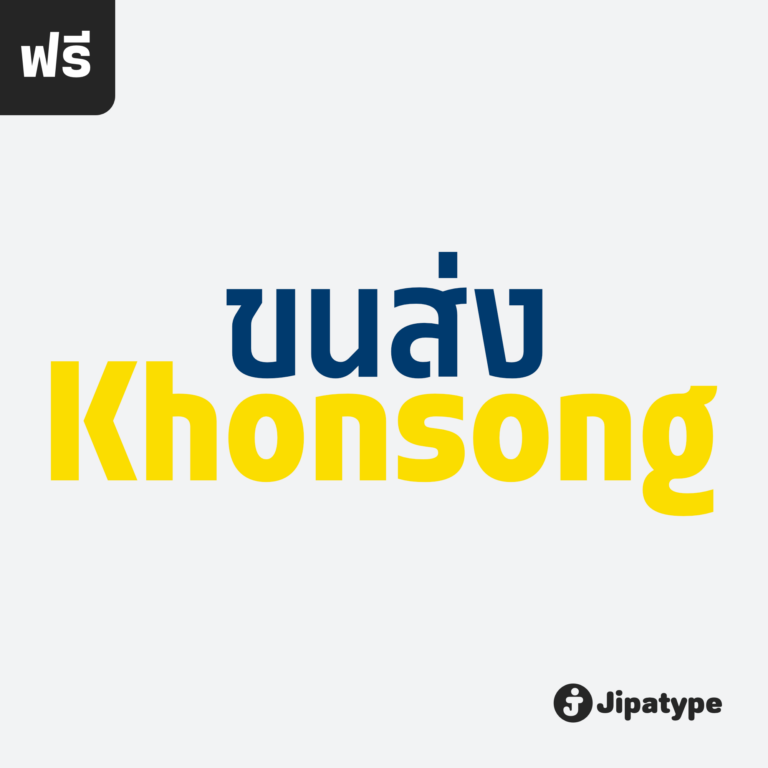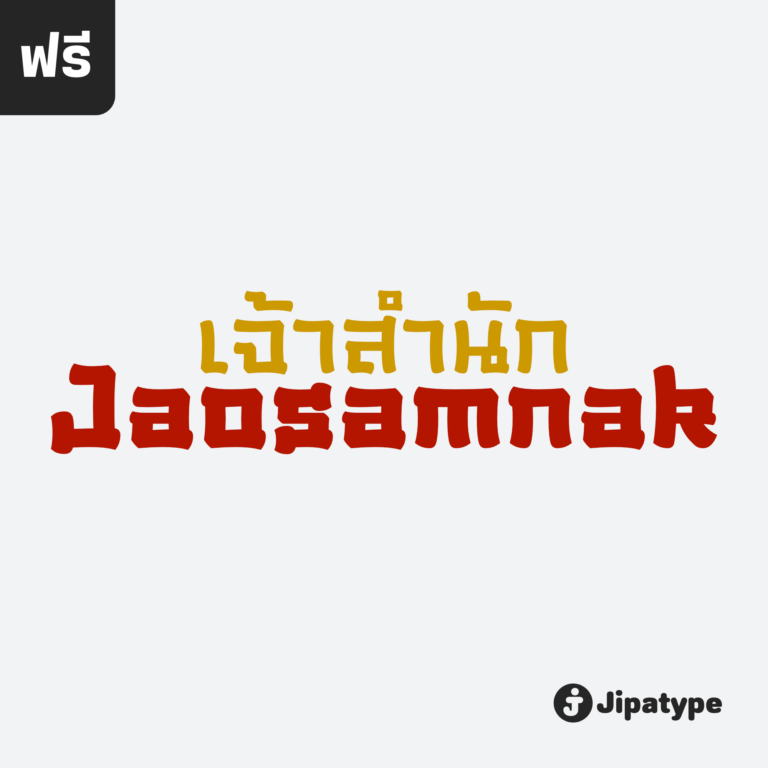
ชีวะเท็กซ์ เรา’ดิด | Chewatext Rounded
Chewatext Rounded เป็นแบบอักษรที่พัฒนาต่อมาจาก Chewatext มีรูปลักษณ์กลมมน เรียบง่าย เรขาคณิต มีให้เลือกใช้ถึง 18 สไตล์ รองรับตัวอักษรลาติน 1 และอักษรไทย เหมาะสำหรับสิ่งพิมพ์ต่าง ๆ ทั้งออนไลน์และออฟไลน์ ออกแบบโดย : อานุภาพ ใจชำนาญ (Anupap Jaichumnan)สามารถใช้งานฟอนต์ได้ฟรีในเชิงพาณิชย์ ผ่านแอปฯ ของจิปาไทป์ ดูรายละเอียดและดาวน์โหลดแอปฯได้ที่ : jipatype.com
ปักษา | Paksa
ปักษา เป็นแบบอักษรซานเซอริฟสำหรับตกแต่ง ชื่อของแบบอักษรนี้มาจากคำไทยที่แปลว่า “นก” ออกแบบโดย : อานุภาพ ใจชำนาญ (Anupap Jaichumnan)สามารถใช้งานฟอนต์ได้ฟรีในเชิงพาณิชย์ ผ่านแอปฯ ของจิปาไทป์ ดูรายละเอียดและดาวน์โหลดแอปฯได้ที่ : jipatype.com
วิจิตรา | Wichittra
วิจิตรา เป็นแบบอักษรเซอริฟแบบแคบคอนทราสต์สูง ชื่อของแบบอักษรนี้มาจากชื่อทั่วไปของผู้หญิงไทย ซื่งมีความหมายว่า ‘สวย’ หรือ ‘งดงาม’ ออกแบบโดย : อานุภาพ ใจชำนาญ (Anupap Jaichumnan)สามารถใช้งานฟอนต์ได้ฟรีในเชิงพาณิชย์ ผ่านแอปฯ ของจิปาไทป์ ดูรายละเอียดและดาวน์โหลดแอปฯได้ที่ : jipatype.com
ชีวะเท็กซ์ | Chewatext
Chewatext เป็นแบบอักษรซานเซอริฟที่มีรูปลักษณ์เรียบง่าย เรขาคณิต และเทคโนโลยี มีให้เลือกใช้ถึง 18 สไตล์ รองรับตัวอักษรละติน 1 และอักษรไทย ทำให้เป็นตัวเลือกที่ดีที่สุดสำหรับโปรเจกต์ร่วมสมัย ไม่ว่าจะเป็นงานสิ่งพิมพ์ต่าง ๆ ทั้งออนไลน์และออฟไลน์ ออกแบบโดย : อานุภาพ ใจชำนาญ (Anupap Jaichumnan)สามารถใช้งานฟอนต์ได้ฟรีในเชิงพาณิชย์ ผ่านแอปฯ ของจิปาไทป์ ดูรายละเอียดและดาวน์โหลดแอปฯได้ที่ : jipatype.com
เจ้าสำนัก | Jaosamnak
ขอแนะนำฟอนต์เจ้าสำนัก แบบอักษรอันงดงามที่ได้รับแรงบันดาลใจจากการประดิษฐ์ตัวอักษรพู่กันจีน ด้วยเส้นโค้งที่สง่างาม เส้นสายที่ลื่นไหล และเรียบง่าย เจ้าสำราญนำความสง่างามเหนือกาลเวลามาสู่การออกแบบของคุณ แบบอักษรนี้เหมาะสำหรับการใช้งานที่หลากหลาย เช่น พาดหัวข้อความ พาดหัวย่อย บรรจุภัณฑ์ โปสเตอร์ และสื่อสิ่งพิมพ์อื่นๆ ออกแบบโดย : อานุภาพ ใจชำนาญ (Anupap Jaichumnan)สามารถใช้งานฟอนต์ได้ฟรีในเชิงพาณิชย์ ผ่านแอปฯ ของจิปาไทป์ ดูรายละเอียดและดาวน์โหลดแอปฯได้ที่ : jipatype.com
ขนส่ง ราวนด์ | Khonsong Rounded
ขอแนะนำฟอนต์ Khonsong Rounded ฟอนต์กลมมนแบบ semi-condensed sans serif ซึ่งผสมผสานความทันสมัย อนาคต และความนุ่มละมุนเข้าด้วยกันอย่างกลมกลืน ด้วยรูปลักษณ์ที่โฉบเฉี่ยวและร่วมสมัย ความกว้างแบบ semi-condensed ทำให้มีความสมดุลที่สมบูรณ์แบบระหว่างการประหยัดพื้นที่และความสามารถในการอ่าน ทำให้เป็นตัวเลือกที่เหมาะสำหรับการใช้งานที่หลากหลาย ตั้งแต่สื่อออนไลน์ไปจนถึงสื่อสิ่งพิมพ์ ออกแบบโดย : อานุภาพ ใจชำนาญ (Anupap Jaichumnan)สามารถใช้งานฟอนต์ได้ฟรีในเชิงพาณิชย์ ผ่านแอปฯ ของจิปาไทป์ ดูรายละเอียดและดาวน์โหลดแอปฯได้ที่ : jipatype.com
ขนส่ง | Khonsong
ขอแนะนำฟอนต์ Khonsong ฟอนต์แบบ semi-condensed sans serif ซึ่งผสมผสานความทันสมัยและอนาคตเข้าด้วยกันอย่างกลมกลืน ด้วยรูปลักษณ์ที่โฉบเฉี่ยวและร่วมสมัย ความกว้างแบบ semi-condensed ทำให้มีความสมดุลที่สมบูรณ์แบบระหว่างการประหยัดพื้นที่และความสามารถในการอ่าน ออกแบบโดย : อานุภาพ ใจชำนาญ (Anupap Jaichumnan)สามารถใช้งานฟอนต์ได้ฟรีในเชิงพาณิชย์ ผ่านแอปฯ ของจิปาไทป์ ดูรายละเอียดและดาวน์โหลดแอปฯได้ที่ : jipatype.com
ทวิลักษณ์ เซอริฟ | Thawilak Serif
ขอแนะนำ Thawilak Serif แบบอักษรที่สวยงามและละเอียดอ่อนที่รวบรวมแก่นแท้ของความสง่างาม และความมั่นคง ด้วยคอนทราสต์สูงและรูปทรงที่กว้าง ฟอนต์นี้มีเสน่ห์เหนือกาลเวลาซึ่งจะสร้างความประทับใจให้กับผู้พบเห็นได้ไม่รู้ลืม Thawilak Serif คือตัวแทนแห่งความงามและความมั่นคง ไม่ว่าจะใช้ในสื่อสิ่งพิมพ์หรือสื่อดิจิทัล จะเพิ่มสัมผัสของความมีระดับและความน่าเชื่อถือให้กับโปรเจกต์ต่างๆ ไม่ว่าจะเป็นบทความ การสร้างแบรนด์ หรือบรรจุภัณฑ์ที่หรูหรา ออกแบบโดย : อานุภาพ ใจชำนาญ (Anupap Jaichumnan)สามารถใช้งานฟอนต์ได้ฟรีในเชิงพาณิชย์ ผ่านแอปฯ ของจิปาไทป์ ดูรายละเอียดและดาวน์โหลดแอปฯได้ที่ : jipatype.com
ทวิลักษณ์ สลับ | Thawilak Slab
ขอแนะนำ “Tawilack Slab” ฟอนต์ serif แบบ slab ที่แสดงถึงความแข็งแกร่งและความมั่นคง ทวีลักษณ์ สลับ มีรูปทรงกว้าง แข็งแรงและมั่นคง คอนทราสต์ต่ำทำให้เกิดความกลมกลืนระหว่างเส้นหนาและเส้นบาง ทำให้ได้แบบอักษรที่สวยงามและอ่านง่าย ด้วยรูปลักษณ์ที่โดดเด่น ทวีลักษณ์ สลับ จึงสมบูรณ์แบบสำหรับโปรเจกต์ที่ต้องการความชัดเจนและมั่นใจ ไม่ว่าจะใช้พาดหัว หรือสร้างแบรนด์ Thawilack Slab ก็สร้างความประทับใจได้ไม่รู้ลืมด้วยรูปลักษณ์ที่แข็งแกร่งและมั่นคงดึงดูดความสนใจ แบบอักษรนี้เป็นตัวเลือกอเนกประสงค์ที่สามารถปรับเข้ากับบริบทการออกแบบต่างๆ ได้อย่างลงตัว ทำให้เป็นคู่หูที่ยอดเยี่ยมสำหรับทั้งสิ่งพิมพ์และสื่อดิจิทัล ออกแบบโดย : อานุภาพ ใจชำนาญ (Anupap Jaichumnan)สามารถใช้งานฟอนต์ได้ฟรีในเชิงพาณิชย์ ผ่านแอปฯ ของจิปาไทป์ ดูรายละเอียดและดาวน์โหลดแอปฯได้ที่ : jipatype.com
หินนวล | Hinnual
Hinnual เป็นฟอนต์ที่ผสมผสานระหว่างรูปทรงสี่เหลี่ยมและทรงกลมเพื่อสร้างสไตล์ที่ไม่เหมือนใคร ชื่อมาจากคำไทย 2 คำ คือ Hin แปลว่า หิน และ Nual แปลว่า อ่อน ผสมผสานองค์ประกอบที่แข็งและอ่อนนี้สะท้อนให้เห็นในแบบอักษร ซึ่งมีเส้นที่สะอาดตาและเส้นคมซึ่งถูกทำให้อ่อนลงด้วยมุมโค้งมน ฟอนต์มีให้เลือกถึง 18 แบบ มีตัวเลือกหลากหลายให้คุณได้เลือกใช้ Hinnual เหมาะอย่างยิ่งสำหรับใช้ในพาดหัวและพาดหัวย่อย ซึ่งลักษณะที่โดดเด่นสามารถช่วยดึงดูดความสนใจของผู้อ่านได้ เส้นสายที่สะอาดตาและสไตล์ที่เป็นเอกลักษณ์ยังทำให้เป็นตัวเลือกที่ยอดเยี่ยมสำหรับแบรนด์ โลโก้ และงานออกแบบอื่นๆ ที่ต้องการภาพลักษณ์ที่น่าจดจำ โดยรวมแล้ว Hinnual เป็นฟอนต์อเนกประสงค์และสะดุดตาที่ผสมผสานองค์ประกอบทั้งความแข็งแกร่งและความนุ่มนวล การออกแบบที่เป็นเอกลักษณ์ทำให้เป็นตัวเลือกที่ยอดเยี่ยมสำหรับนักออกแบบที่ต้องการสร้างผลงานที่น่าจดจำ ออกแบบโดย : อานุภาพ ใจชำนาญ (Anupap Jaichumnan)สามารถใช้งานฟอนต์ได้ฟรีในเชิงพาณิชย์ ผ่านแอปฯ ของจิปาไทป์ ดูรายละเอียดและดาวน์โหลดแอปฯได้ที่ : jipatype.com
พอว์เหมาะ | Pawmor
ขอแนะนำ Pawmor ฟอนต์ sans-serif ใหม่ที่น่ารักและขี้เล่น ซึ่งจะเพิ่มความน่ารักให้กับงานออกแบบของคุณ! แบบอักษรนี้เหมาะสำหรับโปรเจกต์ที่เกี่ยวข้องกับสัตว์เลี้ยงหรือสัตว์ต่างๆ ด้วยขอบที่โค้งมนและส่วนโค้งที่นุ่มนวล ให้ความรู้สึกอบอุ่นและเป็นกันเองจนยากจะต้านทาน Pawmor มีให้เลือกถึง 18 แบบ ให้คุณได้เลือกใช้ตามความต้องการของคุณ ด้วย Pawmor คุณสามารถสร้างงานออกแบบที่สะดุดตาสำหรับธุรกิจเกี่ยวกับสัตว์เลี้ยง งานกิจกรรมต่างๆ เกี่ยวกับสัตว์ โดยรวมแล้ว Pawmor เป็นตัวเลือกที่สมบูรณ์แบบสำหรับทุกคนที่ต้องการเพิ่มความแปลกใหม่และความสนุกสนานให้กับงานออกแบบของคุณ ออกแบบโดย : อานุภาพ ใจชำนาญ (Anupap Jaichumnan)สามารถใช้งานฟอนต์ได้ฟรีในเชิงพาณิชย์ ผ่านแอปฯ ของจิปาไทป์ ดูรายละเอียดและดาวน์โหลดแอปฯได้ที่ : jipatype.com
อธิษฐาน | Athisthan
อธิษฐาน เป็นอักษรแบบคอนทราสต์แซนส์เซอริฟ มาพร้อมกับอักษรแบบมีหัวสำหรับภาษาไทย ดูทางการ เรียบหรู มีเสน่ห์ เหมาะสำหรับการใช้พาดหัว หรือรองพาดหัว มีทั้งหมด 9 น้ำหนักและตัวเอียงของแต่ละน้ำหนักรวมทั้งหมดมี 18 สไตล์ และมีฟีเจอร์อื่น ๆ เช่น Small Caps และฟีเจอร์อื่น ๆ พร้อมให้คุณได้เลือกใช้งาน รองรับหลากหลายภาษา ออกแบบโดย : อานุภาพ ใจชำนาญ (Anupap Jaichumnan)สามารถใช้งานฟอนต์ได้ฟรีในเชิงพาณิชย์ ผ่านแอปฯ ของจิปาไทป์ ดูรายละเอียดและดาวน์โหลดแอปฯได้ที่ : jipatype.com